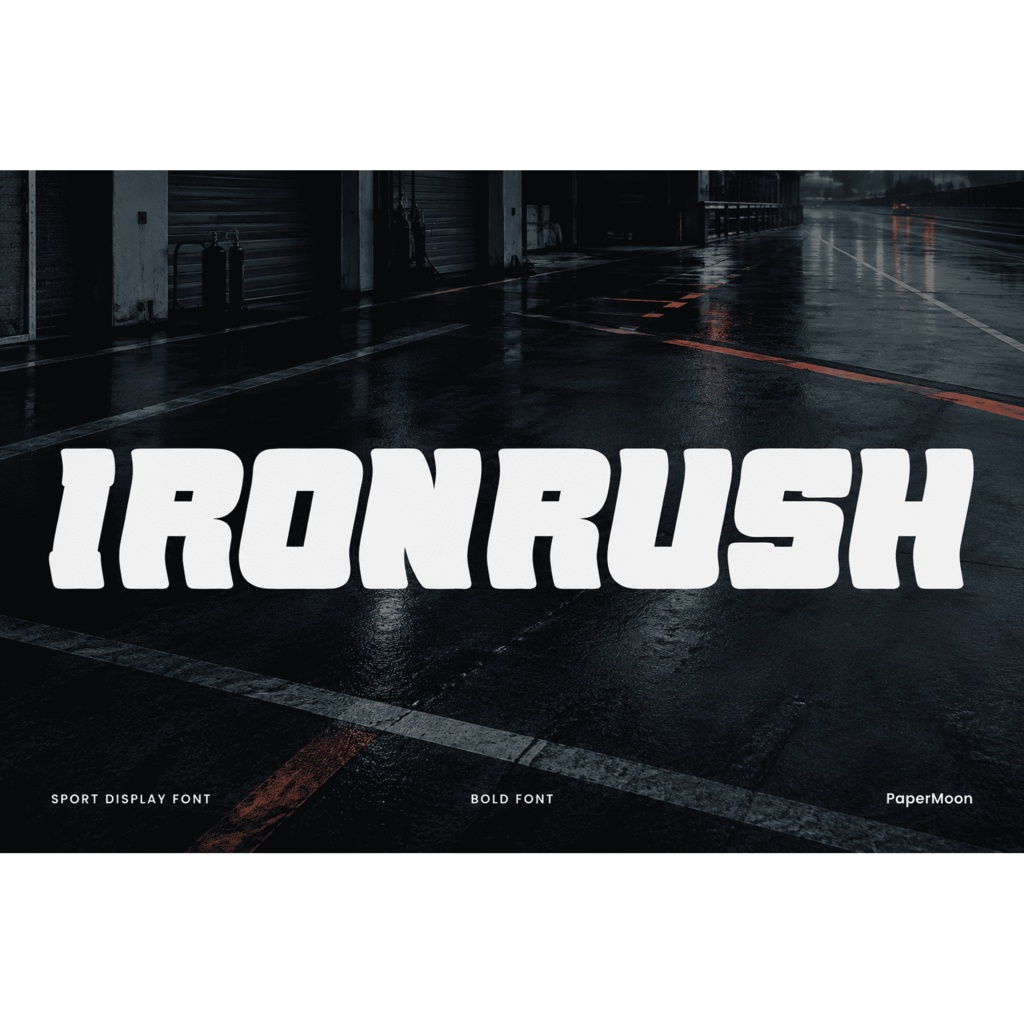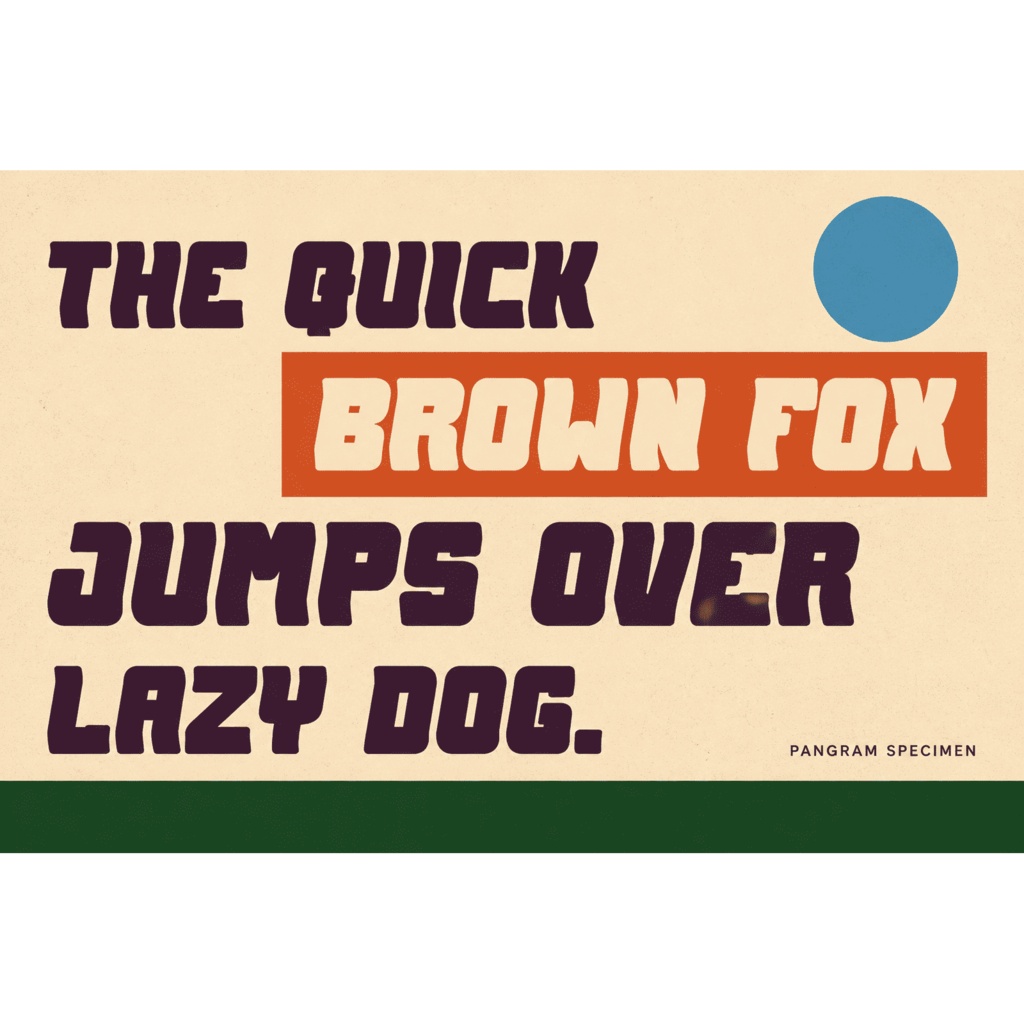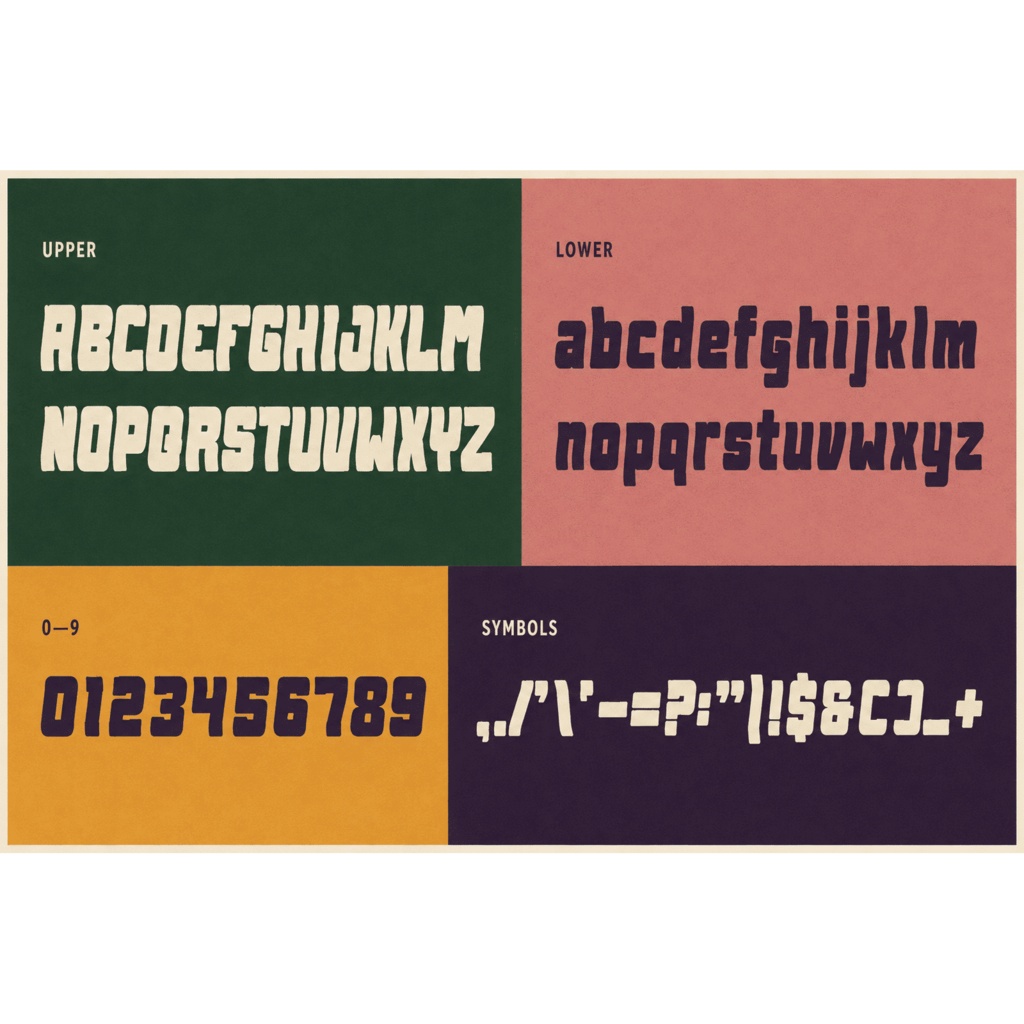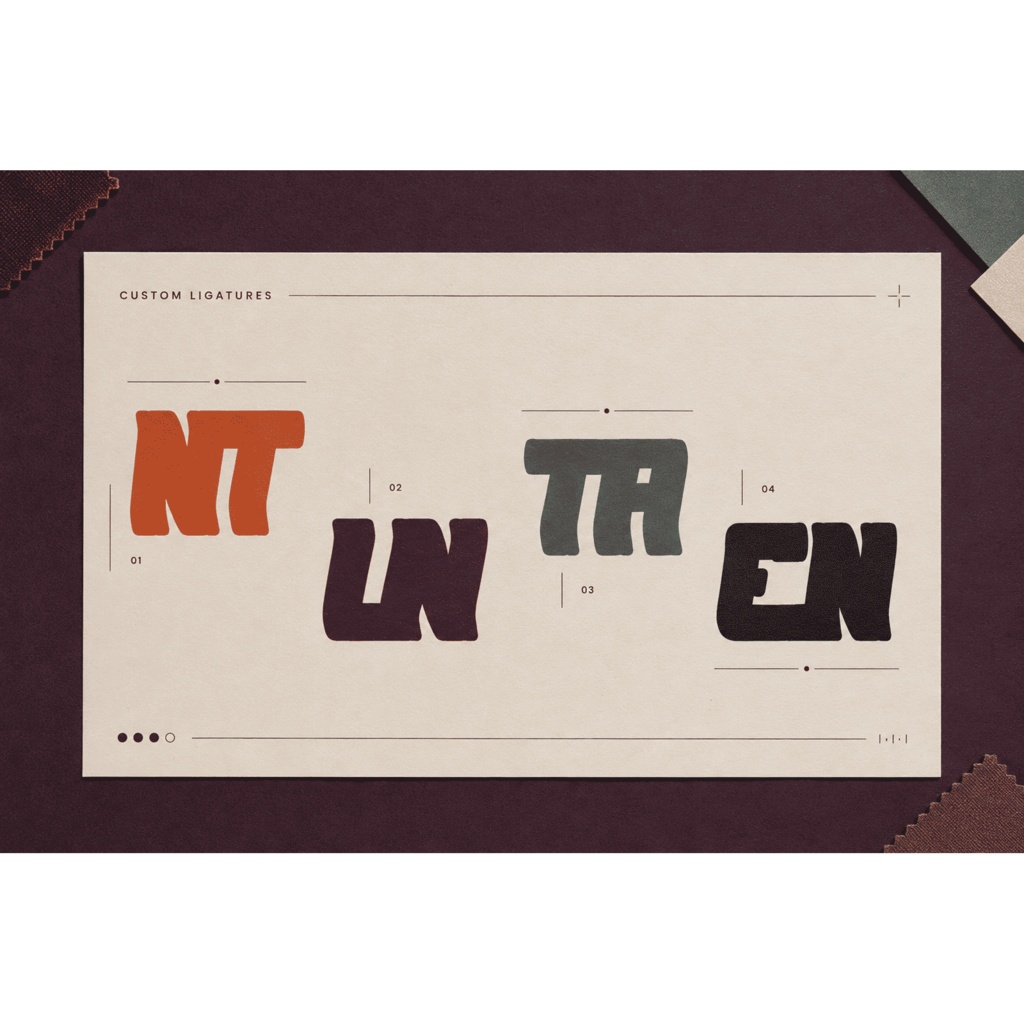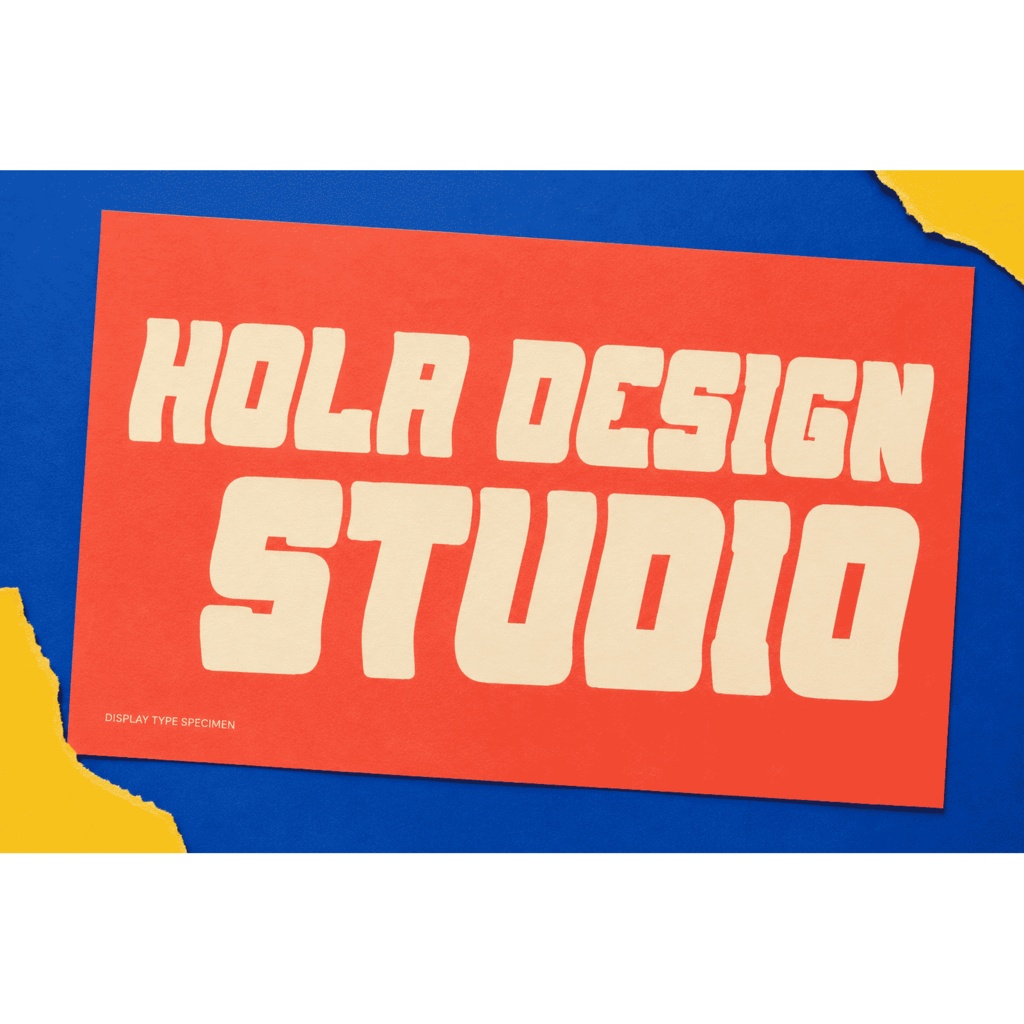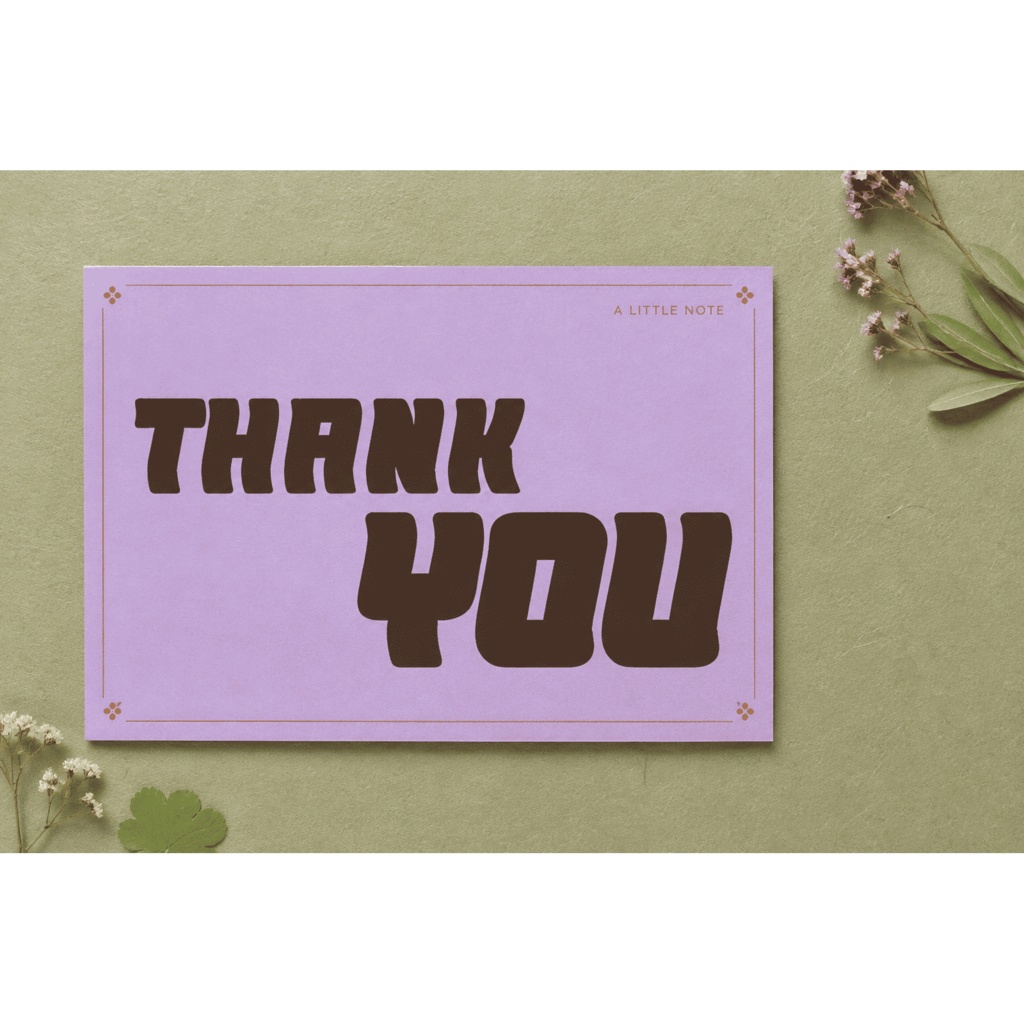
IronRush | スポーツ・ジム向けボールド欧文フォント | ロゴ・ポスター・グッズ用 Display Font
IronRush(アイアンラッシュ)は、ジム・スポーツ向けにデザインされたボールドなディスプレイ用欧文フォントです。太く力強いストロークで、フィットネスブランディング、チームロゴ、スポーツウェア、大会ポスター、映画タイトルなど、遠くからでもはっきり読めるインパクト重視の見出しに最適です。1ウエイト(Regular)・4形式(OTF / TTF / WOFF / WOFF2)でお届けします。 ### 収録内容 - 1スタイル(Regular)— 4形式: OTF / TTF / WOFF / WOFF2(IronRush-Regular) ### 対応文字 - Basic Latin のみ: A–Z・a–z・数字(0–9)・記号 - 日本語・かな・漢字は含まれません。Cyrillic / Greek も未収録です。ラテン文字専用の書体です。 - OpenType 機能: カーニング(kern)・標準合字(liga) ### 用途 - ジム・フィットネスのブランディング・プロモーション - チームロゴ・スポーツウェア・アパレル - スポーツ大会・イベントのポスター・フライヤー - 映画タイトル・アルバムジャケット - ロゴ・ラベル・商品パッケージ - ゲーム・eスポーツのバナー・サムネイル ### 形式 - IronRush-Regular.otf / IronRush-Regular.ttf(デスクトップ・印刷・DTP アプリ) - IronRush-Regular.woff / IronRush-Regular.woff2(Web サイト・@font-face) ### 対応環境 - Windows / macOS。Adobe Photoshop / Illustrator / InDesign、Affinity、Figma、Canva、Procreate、Cricut Design Space、Silhouette Studio など OTF/TTF 対応アプリ全般。Web プロジェクトは WOFF/WOFF2。 ### 利用許諾 - 商用ライセンスの内容は、同製品の姉妹プラットフォーム向けリスト(Creative Market・MasterBundles・Cubebrush)に明記されています。BOOTH 出品時は、ライセンス種別の選択と購入者向けライセンス文面の掲載が必要です(出品者操作)。本コピーはライセンス文言そのものではなく、ライセンス条件の詳細は BOOTH 側での選択・確認が必要です(本コピー作成時点では未確認 — 出品者が確認・記載してください)。